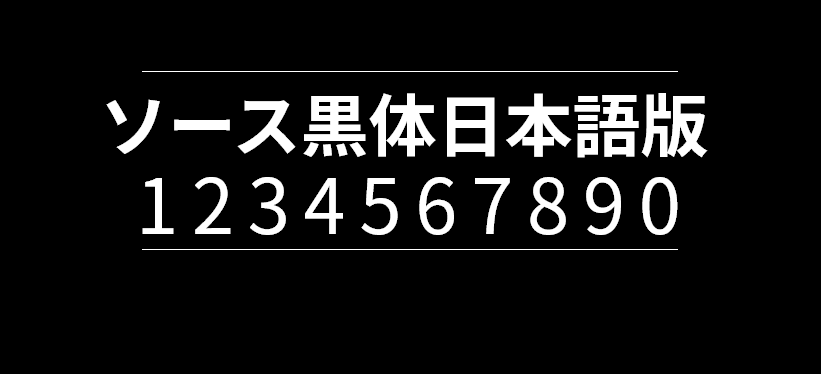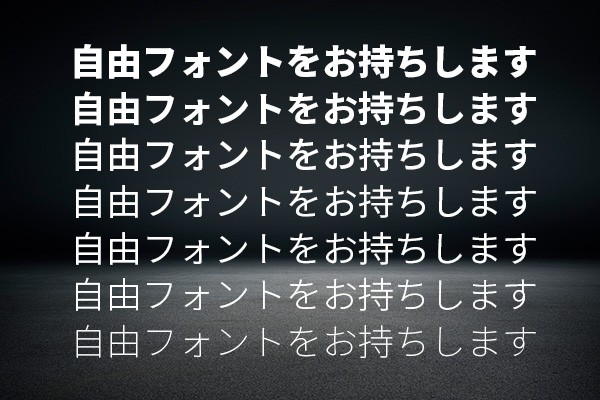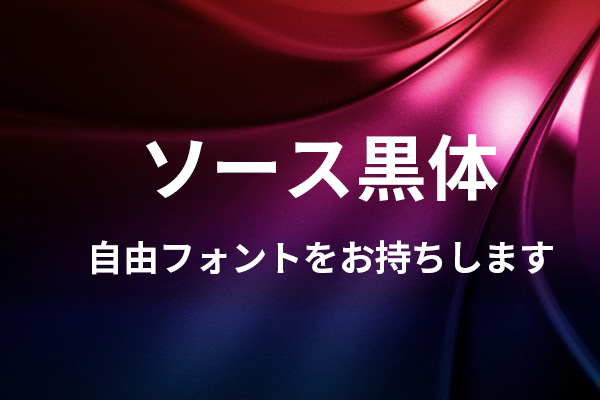
思源黑体-日文版
是由adobe与谷歌领导开发的开源字体,从2014年至今经过不断的修正与完善,影响越来越大,像思源柔黑、思源真黑等字体就是此开源的基础上衍化而来的,实用性非常高。 有七种字体粗细(ExtraLight、Light、Normal、Regular、Medium、Bold 和 Heavy),完全支持日文、韩文、繁体中文和简体中文,还包括来自 Source Sans字体家族的拉丁文、希腊文和西里尔文字形共65536个字形。Google将其命名为Noto SansCJK,作为Google的Noto字体家族的成员。Adobe则命名为Source Han Sans,作为Adobe的Source字体家族的一员。Adobe拥有字体设计的版权。发布的字体文件则可以不受限制的免费使用。 安装后软件中找不到的话,可以找“源ノ角ゴシック JP”或“Source Han Sans JP”。